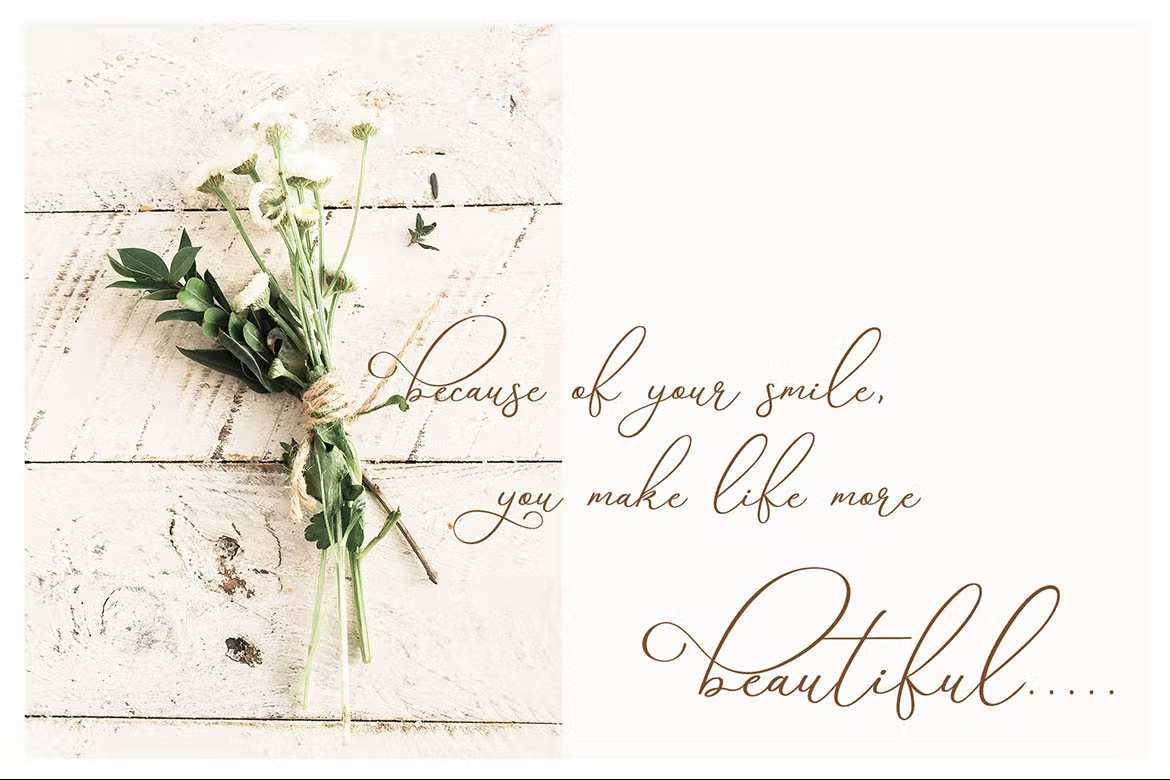
Avelline Font
Description de Avelline Font
Avelline est une police de calligraphie moderne. C’est génial pour votre projet, signature élégante, signature photographique, belles citations, image de marque cosmétique ou tout beau projet de design.